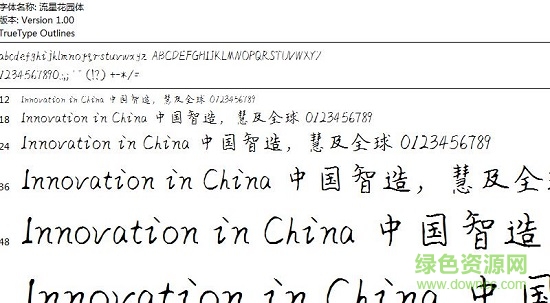
流星花園字體是一款鋼筆書法字體,從這款字中能清晰的看出作者扎實(shí)的書法功底,并且這款字要是用在手機(jī)上還會(huì)呈現(xiàn)彩色的形態(tài),喜歡的朋友趕緊下載!
流星花園字體是一款采用手寫書法打造而來的字體,這款字體的字跡端正簡潔,并且每一筆每一劃都十分的用心,創(chuàng)作出來的效果整體就會(huì)很亮眼!